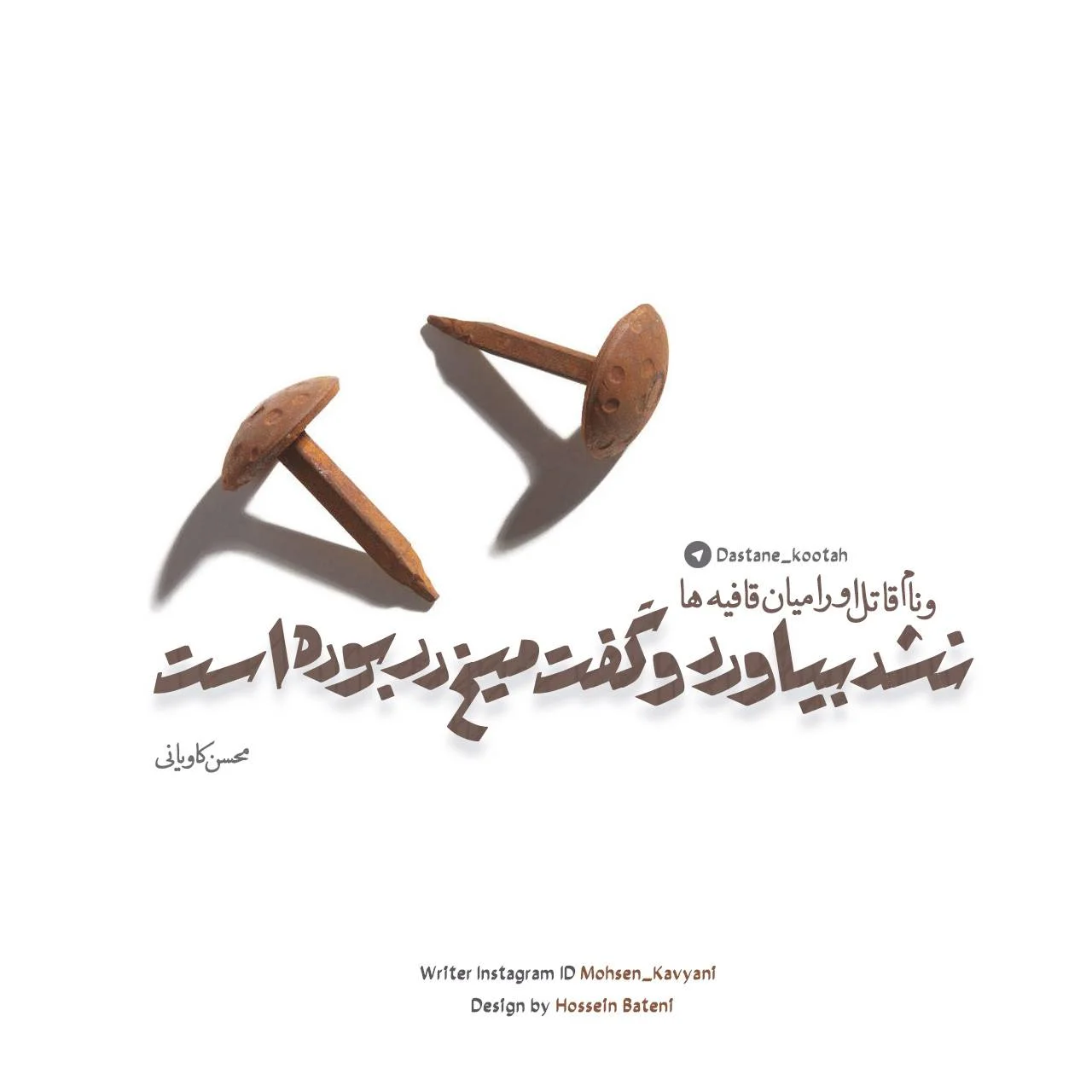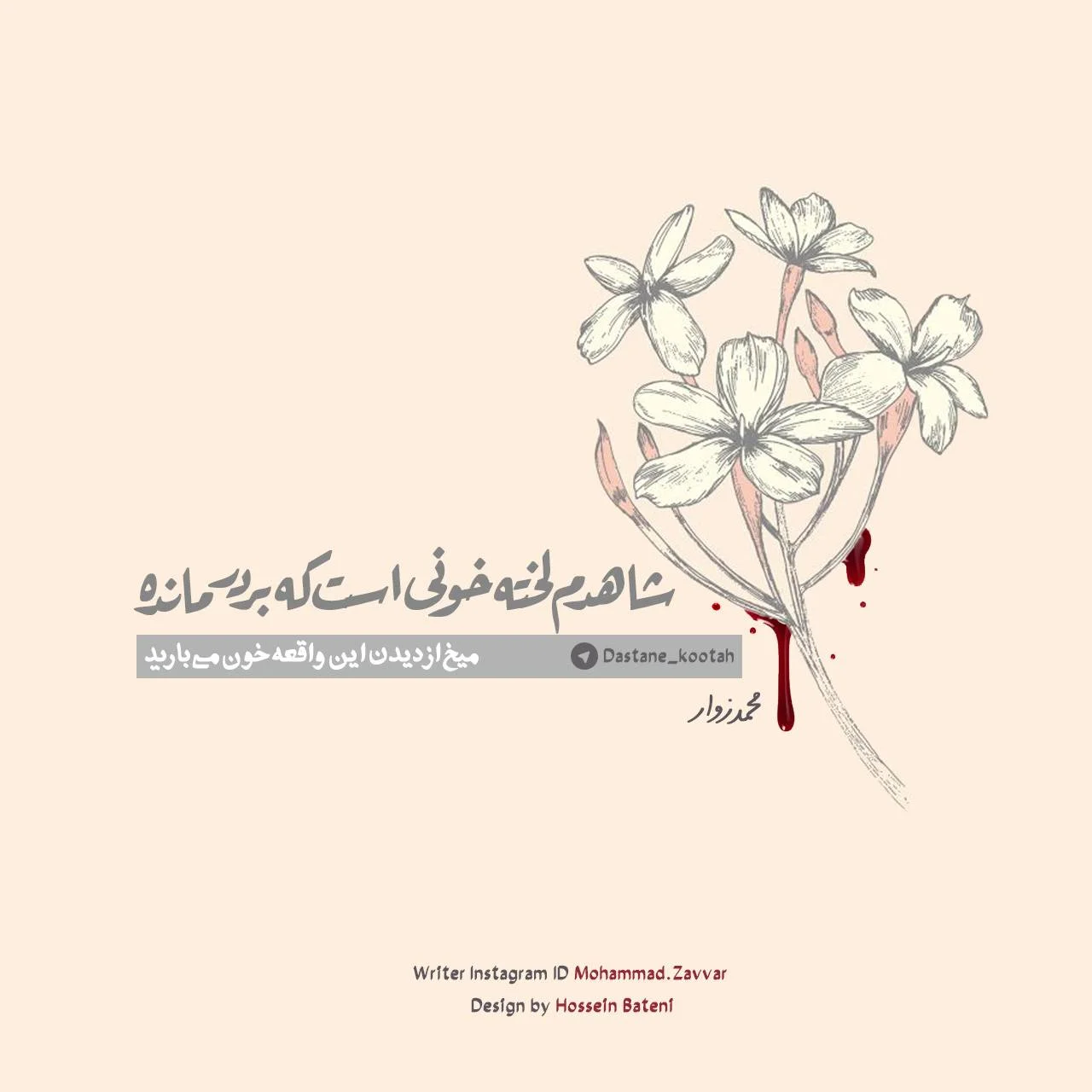
دانلود فونت کوفی الرقعة – Ruqaa Font
فونت کوفی الرقعة
اینبار با فونت عربی الرقعة قلمی که در عناوین سینما و تلویزیون به شما کمک میکند تا زیباتر دیده شوید ، فونتی  که فقط مختص به بولد نویسی نیست و در متون ریز هم به شما کمک میکند و رضایت بینایی شما را جلب میکند ، نام لاتین این فونت Ruqaa Font است
این خط به طور گسترده ای در کشورهای عربی مورد استفاده قرار میگیرد
فونت کوفی الرقعة یک فونت عربی دیگری است که در ایران فونت برای کاربران خوب ایرانی معرفی میشود. امیدواریم از تایپ با آن لذت ببرید. و همچنین برای شما عزیزان پرکاربرد و مفید باشد.